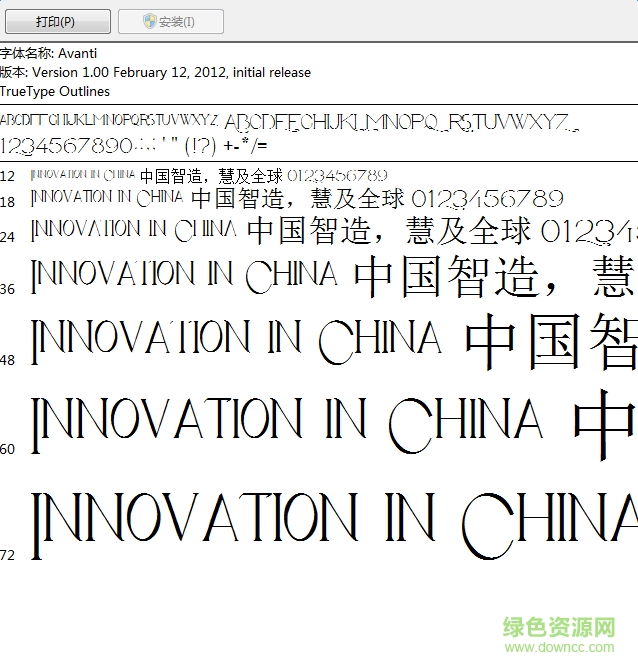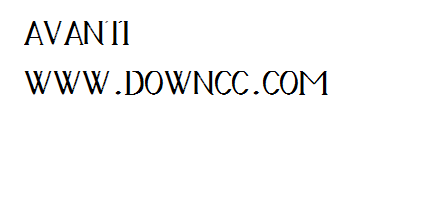
avanti字體是一款英文字體軟件,字體筆畫比較有創(chuàng)意,整體效果十分灑脫,在英文標題內(nèi)容的設(shè)計上有著不錯的應(yīng)用,更多好看的中英文字體盡在綠色資源網(wǎng)!
avanti字體是一款應(yīng)用于藝術(shù)設(shè)計方面的簡體英文字體,該字體筆畫細膩,尾部的甩尾有力且有豐富的筆觸細節(jié),大字效果突出且引人注目;并且最大程度還原作者書寫字形,細節(jié)表現(xiàn)完整,且字庫完整,可以廣泛應(yīng)用于名片設(shè)計、新聞媒體、宣傳海報、ppt、影視制作以及內(nèi)容用字等領(lǐng)域。
avanti英文字體是一類優(yōu)雅正規(guī)字體,字體比較時尚潮流,整體效果非??犰?,深受廣大年輕人喜愛!